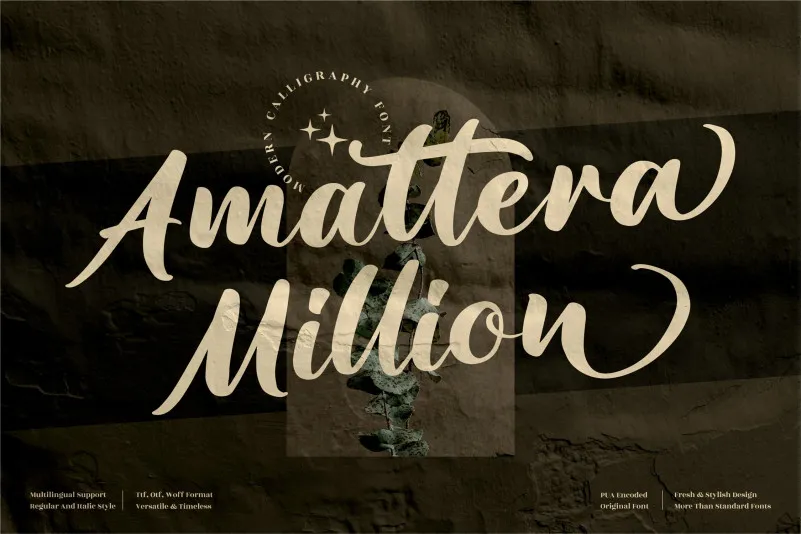
Amattera Million Font – Download Grátis
A fonte Amattera Million é uma escolha perfeita para quem busca adicionar um toque sofisticado a seus projetos digitais e impressos. Conhecida como uma fonte de assinatura premium, ela se adapta perfeitamente a uma variedade de usos, desde logotipos e projetos de marca até produtos feitos à mão e embalagens de produto. Essa font é ideal para criar designs que chamem a atenção, seja em têxtil, impressão digital ou papel. Ideal tanto para um projeto convencional quanto para aqueles com personalidade única, como etiquetas especiais, camisetas e até mesmo assinaturas de livros, o Amattera Million oferece uma textura sofisticada que adicionará valor a qualquer trabalho. Essa font é perfeita para quando você quer criar algo impecável, seja um projeto exclusivo ou um item personalizado de luxo. Com sua design limpo e elegante, a Amattera Million pode ser usada em vários tipos de projetos, incluindo posteres e cartazes, adesivos e até mesmo tags de câmeras. A fonte é especialmente adequada para criar uma identidade visual forte e coesa, tornando-a um investimento valioso para qualquer designer ou empreendedor que busca dar seu trabalho um aspecto único e memorável. Com Amattera Million na sua arsenal de ferramentas de design, você estará sempre pronto para capturar a atenção do seu público alvo com uma escolha de fontes de alta qualidade.